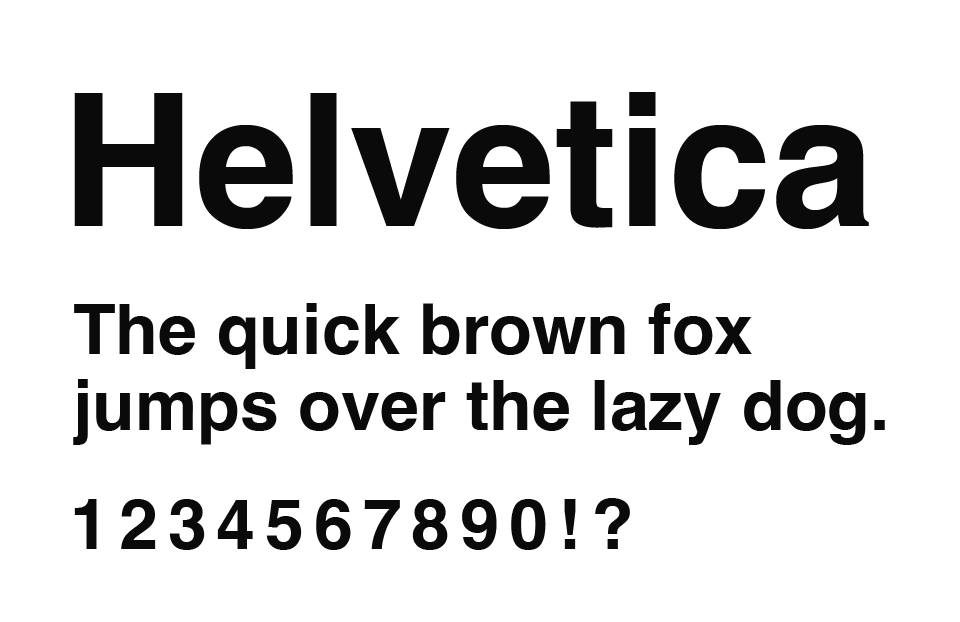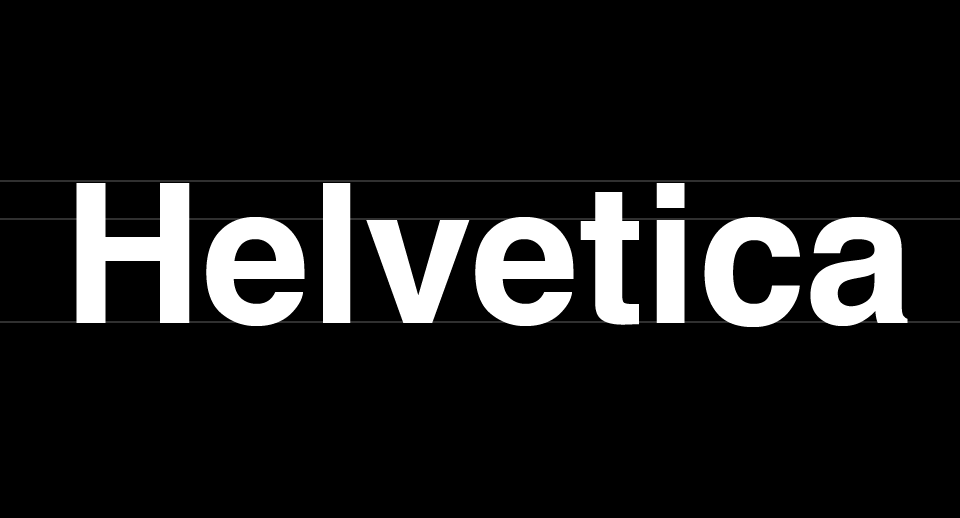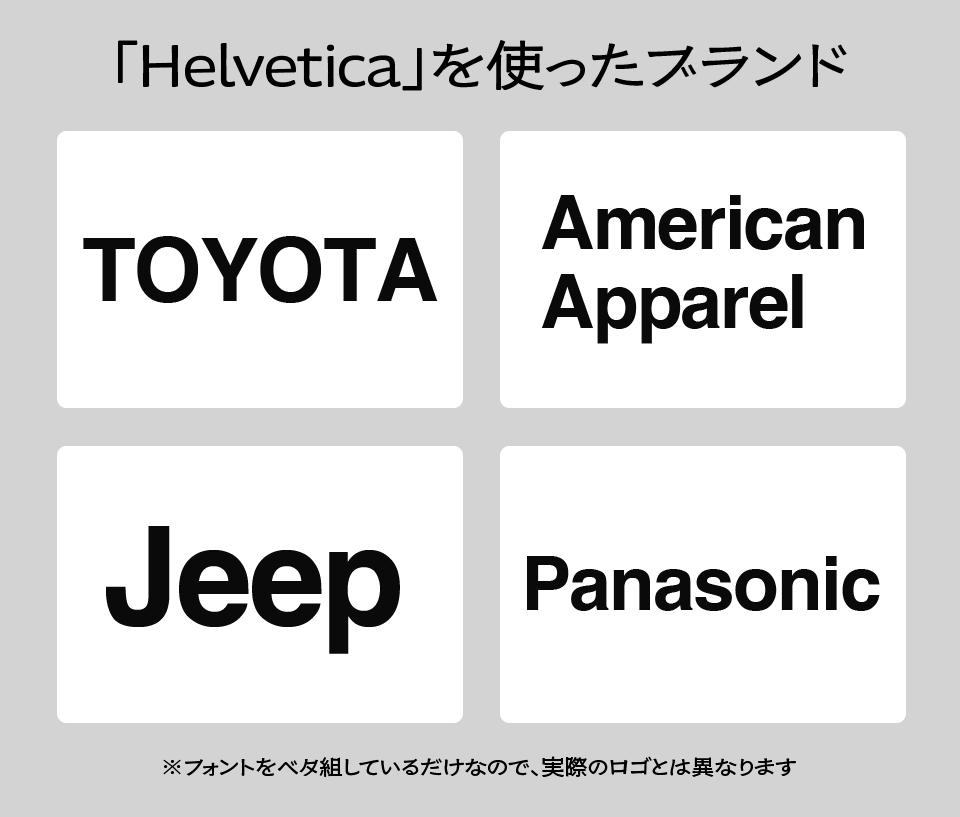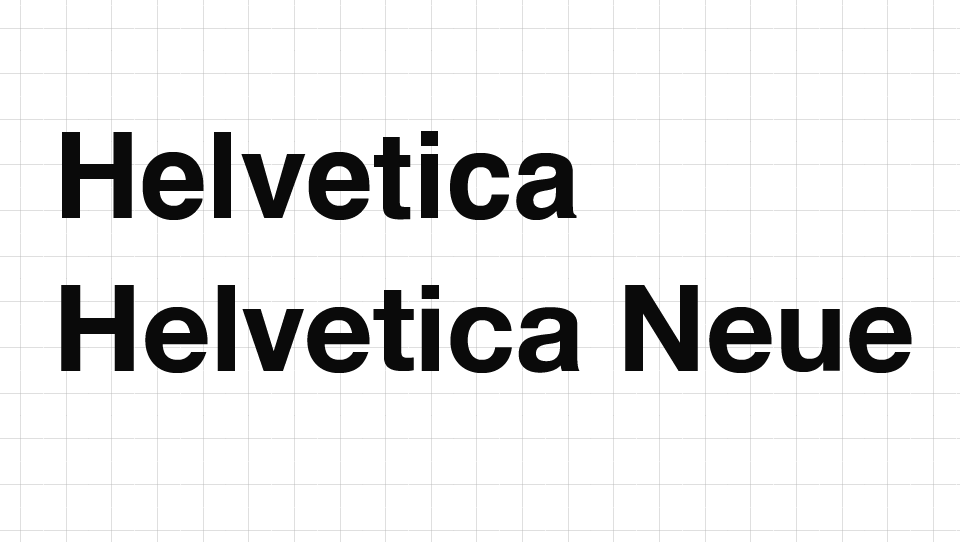
「Helvetica (ヘルベチカ)」の魅力とは?いまも世界で愛され続けるフォントの1つ
世界中で愛され続ける定番フォント「Helvetica(ヘルベチカ)」。
シンプルでクセがなく、どんな場面でも自然に馴染むその佇まいは、まさに“フォント界のスタンダード”とも言える存在です。グラフィックデザインやWeb制作、看板や広告、企業ロゴなど、私たちの生活の中でいつのまにか目にしているHelvetica。
その魅力は見た目の美しさだけでなく、歴史や思想にも深く根ざしています。
本記事では、Helveticaの誕生から現代に至るまでの進化、特徴や類似フォント、ロゴ事例、さらには映画・漫画での登場までを幅広く紹介。なぜこのフォントが世界中で使われ続けているのか、その理由をあらためてひも解いていきます。
Helvetica (ヘルベチカ) とは
Helvetica(ヘルベチカ)は、シンプルで洗練されたデザインが特徴のサンセリフ体フォントで、世界中のグラフィックデザイナーや企業から長年にわたって愛されています。
そのクリーンで中立的な印象は、時代やトレンドに左右されず、ブランドや情報をすっきりと伝える力に優れています。
フォント名の「Helvetica」は、ラテン語で「スイスの」という意味を持ち、まさにその名の通り、スイスで誕生したフォントです。読みやすさと普遍的なデザインを両立したこのフォントは、現代デザインにおける“基礎中の基礎”とも言える存在です。
まさにフォントの王様。The King of Fontsです。
Helvetica (ヘルベチカ) の歴史
Helveticaは1957年、スイスのタイポグラファーであるマックス・ミーディンガー(Max Miedinger)とエドゥアルト・ホフマン(Eduard Hoffmann)によって、ハース社(Haas Type Foundry)で開発されました。当初の名称は「Neue Haas Grotesk」でしたが、国際的な展開を見据えて、1960年に「Helvetica」という名前に改名されました。
20世紀半ば、欧米では視認性が高く中立的なデザインが求められる時代が到来し、Helveticaはそのニーズに完璧にマッチ。特にスイスの「インターナショナル・タイポグラフィ・スタイル(スイス・スタイル)」の流れを汲んだデザイン界では欠かせないフォントとして定着しました。
スイスデザインを元にしたポスターデザインが閲覧できるサイトでも見てみても、「Helvetica」が多く使われています。グラフィックの参考にもなるので、ぜひチェックしてみてください。
Helvetica (ヘルベチカ) の特徴
Helveticaの最大の特徴は「中立性と可読性」にあります。字形は幾何学的でバランスが取れており、クセがなく、どんな媒体にも馴染みやすい設計になっています。縦横のストロークに太さの差が少なく、文字の高さ(xハイト)も大きめに設計されているため、小さなサイズでも読みやすく、印刷物・看板・ウェブのいずれでも視認性を保てます。
また、カウンター(文字の内側の空間)や字間も絶妙に設計されており、文字列として並んだときにも統一感があり美しく見えます。装飾性を排除したミニマルなデザインであるがゆえに、時代や文化背景に左右されにくい、普遍的な魅力を持っています。
Helvetica (ヘルベチカ) の類似・代替えフォント
代表的な代替フォントには以下のようなものがあります。
- Arial
Microsoftが標準搭載しているサンセリフ体。Helveticaに非常に似ているが、字形に微妙な違いがある。 - Nimbus Sans
オープンソースで使用可能なフォント。Helveticaとの類似性が高く、商用利用にも適しています。 - Open sans
Google Fontsとして提供されている自由なフォント。 - Roboto
Google Fontsとして提供されているGoogleが開発したフォント。
プロジェクトの予算や配布媒体に応じて、これらの代替フォントを使い分けるのも一つの手です。
Helvetica (ヘルベチカ) を使用した身近な企業ロゴ
Helveticaの中立性と信頼感のあるデザインは、多くの大企業が自社のロゴタイプに採用する理由となっています。特に、製品やサービスの信頼性を訴求したいブランドにとっては理想的なフォントです。
たとえば、以下のような企業がHelveticaをロゴに使用しています。
- Lufthansa(ルフトハンザ航空)
- BMW
- Nestlé
- TOYOTA
- American Apparel
- Jeep
- Panasonic(パナソニック)
- Microsoft(旧ロゴ)
どれもグローバルに展開しているブランドばかりであり、Helveticaの普遍性・視認性の高さがいかに信頼されているかがよくわかります。
実際にはHelveticaをベースとして、ブランドごとに細かく調整されていたりする場合もあります。
Helvetica (ヘルベチカ) は映画や漫画にもなっている
Helveticaは単なるフォントの枠を超え、カルチャーの一部としても注目されています。
2007年には、Helvetica誕生50周年を記念して制作されたドキュメンタリー映画『Helvetica』が公開されました。この映画では、世界の有名デザイナーたちが登場し、Helveticaがいかに現代のビジュアル文化に影響を与えてきたかを語ります。
また、日本の漫画作品『ヘルベチカ』では、フォントを擬人化したキャラクターが登場するなど、ユニークな形でも取り上げられています。文字やタイポグラフィの世界を深く掘り下げるきっかけとなる作品として、デザイン好きにはたまらない内容です。
Helveticaのバリエーションと進化「Neue Helvetica・ Helvetica Now」
Helveticaは誕生以来、時代に合わせてアップデートされてきました。その代表例が以下の2つです
- Helvetica Neue(ヘルベチカ・ノイエ)
1983年にリリースされた改訂版。より一貫性のあるデザインとウェイトの拡張が加えられ、現代の印刷やデジタル環境に適応しています。 - Helvetica Now
2019年にMonotype社が発表した最新版。ディスプレイ向け、テキスト向け、マイクロサイズ向けと3種類に分かれており、あらゆるメディアでの使用を意識した設計が特徴です。
このように、Helveticaはただの“昔の定番フォント”ではなく、進化を続ける現役のデザインツールなのです。時代にフィットするようにアップデートされているのもすごいですよね、王様たる所以です。
Helveticaを使うときの注意点
どんなに優れたフォントでも、使いどころを間違えると“無難すぎる”印象や“没個性的”と受け取られることもあります。特に、独自性を前面に出したいブランドやプロダクトにおいては、Helveticaの中立性が逆にマイナスに働くケースもあるかもしれません。
まとめ:Helveticaが愛され続ける理由
Helveticaは「目立たないこと」で目立つ、そんな特異なフォントです。情報をクリアに、誤解なく伝えることを最優先するデザインシーンにおいて、その中立的な美しさは他の追随を許しません。
70年以上にわたり世界中で使用され続けてきたこのフォントは、これからもさまざまなメディアやブランドに採用されていくことでしょう。デザインに関わるすべての人にとって、一度はしっかり向き合いたい“永遠のスタンダード”とも言える存在です。
個人的にもこれからもHelveticaが大好きです。